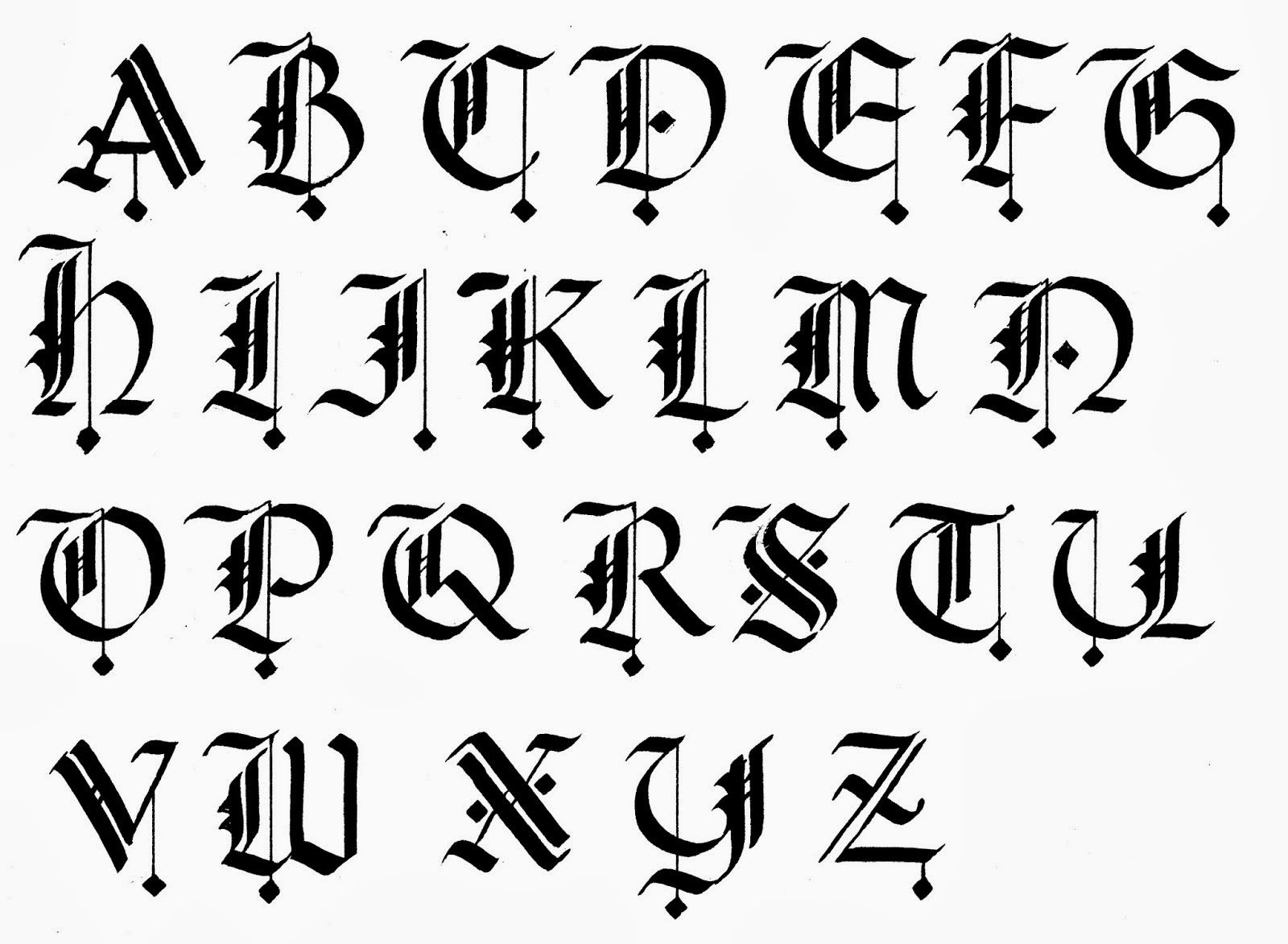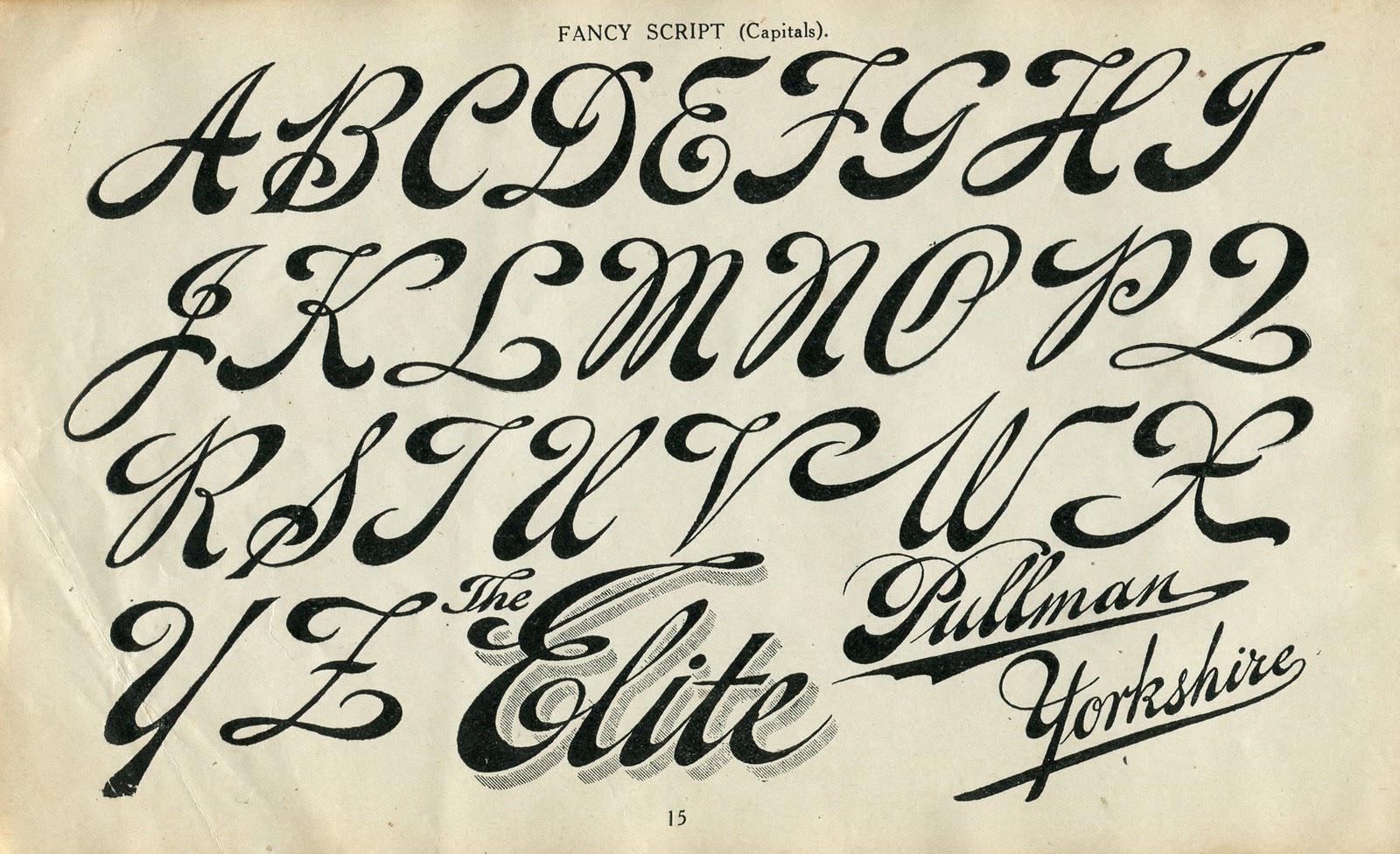
Исторические почерки
Старославянские
К этой группе относятся шрифты, по рисунку имитирующие средневековые кириллические почерки ширококонечным пером, распространенные в X-XVIII веках главным образом в восточной и южной Европе. Существует четыре основных вида кириллических почерков: устав, полуустав, скоропись, вязь, а также их переходные формы. Первые наборные кириллические шрифты XV-XVI века повторяли форму рукописного полуустава. После реформы Петра I начала XVIII века полууставные шрифты сохранились только для церковного употребления. Позднее на основе исторических форм появились стилизации старославянских шрифтов. Сейчас применяются в основном как акцидентные.
Готические
К этой группе относятся шрифты, по рисунку имитирующие средневековые рукописные почерки ширококонечным пером, распространенные в XIII-XVI веках главным образом в северной Европе. Их буквы характеризуются, как правило, узкими пропорциями, сильным контрастом, изломами штрихов, большой насыщенностью и высокой декоративностью.
Существует несколько основных форм готических почерков: текстура, ротунда, бастарда, швабахер, фрактура, канцлей. Первые наборные шрифты XV века повторяли форму наиболее распространенных готических почерков и в дальнейшем применялись параллельно с наборной антиквой, практически выйдя из широкого употребления только в ХХ веке. Сейчас применяются в основном как акцидентные.
Исторические стили
Шрифты, имитирующие наборные или рисованные шрифты определённой эпохи, не вписывающиеся в рамки привычной классификации, в том числе, например:
Итальянские шрифты
Акцидентные шрифты с обратным контрастом, у которых горизонтальные штрихи толще вертикальных. Появились в первой половине XIX века, но пользовались также большой популярностью в конце XIX – начале ХХ века как акцидентные. Иногда их относят к классу брусковых шрифтов. Как правило, в этих шрифтах нет наклонных начертаний.
Акцидентные шрифты с преувеличенными засечками треугольной формы, иногда скругленными в месте примыкания к основному штриху.
Изобретены в Англии в первой половине XIX века.
Шрифты стиля модерн
Акцидентные и текстовые шрифты, появившиеся в конце XIX – начале ХХ века, или разработанные позже в духе эстетики стиля Art Nouveau (Jugendstil, Secession). Отличительные признаки: измененные пропорции, смещенная средняя линия, текучие формы, нарочито преувеличенные элементы, отказ от классических принципов построения, поиск новых форм.
Акцидентные шрифты, характерные для начала 20-х годов ХХ века или разработанные позже в духе эстетики стиля Art Deco, с преувеличенным контрастом или с измененными пропорциями.
Обычно такие шрифты не имеют ни наклонных, ни курсивных начертаний.
Шрифты стиля оп-арт
Руководство по распознаванию стилей шрифтов
Научиться различать стили шрифтов, было одной из самых сложных задач, когда я только начинал работать дизайнером. Будучи самоучкой, единственное существенное отличие, которое я видел, было то, что шрифт был либо с засечками (serif), либо без них (sans serif). Но чем больше я изучал, тем больше понимал, насколько широка вселенная стилей шрифтов.
Это руководство является выдержкой из главы 3 из книги «Лучшая веб-типография для лучшей сети», автор Matej Latin.
Теперь я знаю, почему так сложно распознать стиль шрифта. Когда дело доходит до типографики, особенно если речь идет о шрифтах, все дело в деталях. Трудно даже представить, сколько работы уходит на разработку шрифта и сколько дизайнеров вкладывают свой труд в мельчайшие детали, которые остаются незаметными для большинства людей. Таким образом, чтобы найти ключевые моменты, позволяющие различать стили шрифтов, нам нужно научиться видеть эти детали. Но для начала, для чего вам нужно распознавать стили шрифтов? Почему бы просто не выбрать и не комбинировать шрифты, основываясь на внутреннем чувстве стиля и эстетики?
Ну, вы можете так и поступить. На самом деле я так делал долгое время, особенно в начале моей карьеры. Но у меня была огромная проблема. Я никогда не был уверен в своих решениях при выборе шрифта, и что разработанная мной комбинация шрифтов хорошо взаимодействует между собой. Конечно, вы можете копировать другие или использовать самые популярные шрифты, основываясь на таких классификациях, как Top 10 самых популярных гарнитур Typewolf в 2019 году.
Вот тут-то и появляется необходимость распознавать стили шрифтов. Когда вы можете это делать и знаете, какая история стоит за конкретным стилем, вы можете принимать более удачные решения. Вы можете принять обоснованное решение о выборе следующего шрифта для проекта веб-дизайна, над которым вы работаете. Вы можете лучше комбинировать 2 или более стилей шрифта, потому что вы знаете, какие стили совместимы, а какие нет. Давайте посмотрим на наиболее распространенные стили шрифтов, как они появлялись и функционировали, и посмотрим, что определяет эти стили и истории, стоящие за ними.